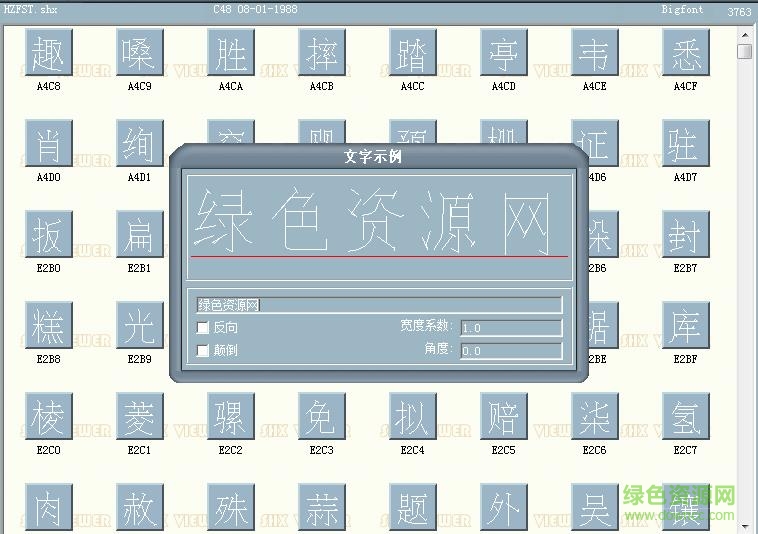
hzfst.shx字體
hzfst.shx字體的獨(dú)特風(fēng)格在用戶進(jìn)行制圖的時(shí)候受到了獨(dú)特最廣泛的運(yùn)用,讓你在cad圖紙中時(shí)常都能夠發(fā)現(xiàn)這款字體的身影,是一款比較使用的cad字體,快來綠色資源網(wǎng)下載吧!
hzfst.shx小編點(diǎn)評
hzfst.shx在一般的工業(yè)制圖,以及矢量圖繪制,商業(yè)制圖,二位平面制圖中都能夠帶來十分優(yōu)質(zhì)的顯示效果,即給設(shè)計(jì)師們不錯(cuò)的體驗(yàn)也給觀看者獨(dú)家欣賞體驗(yàn)!
hzfst.shx字體介紹